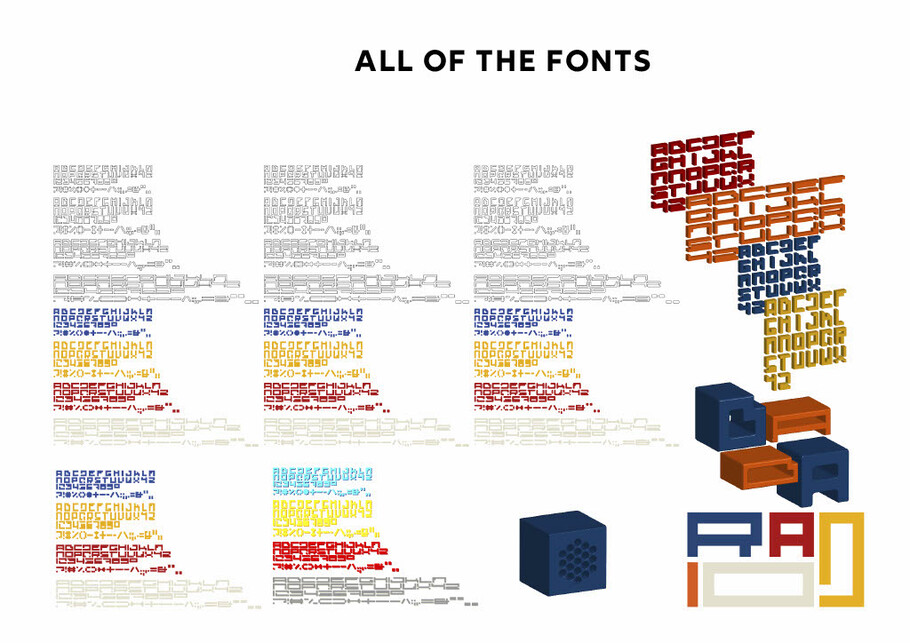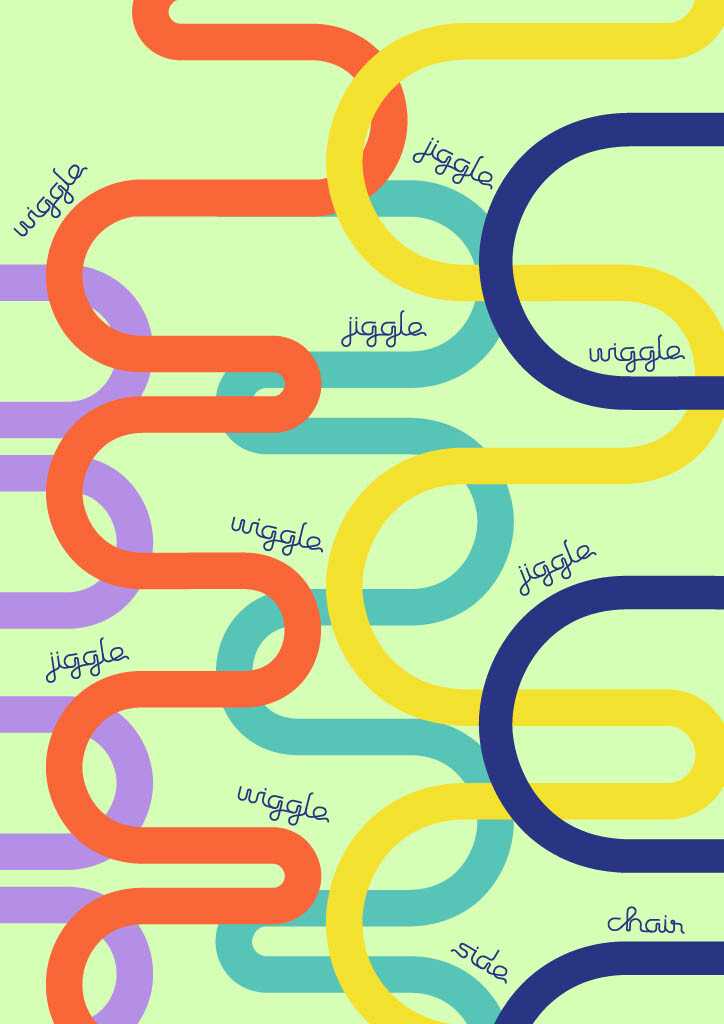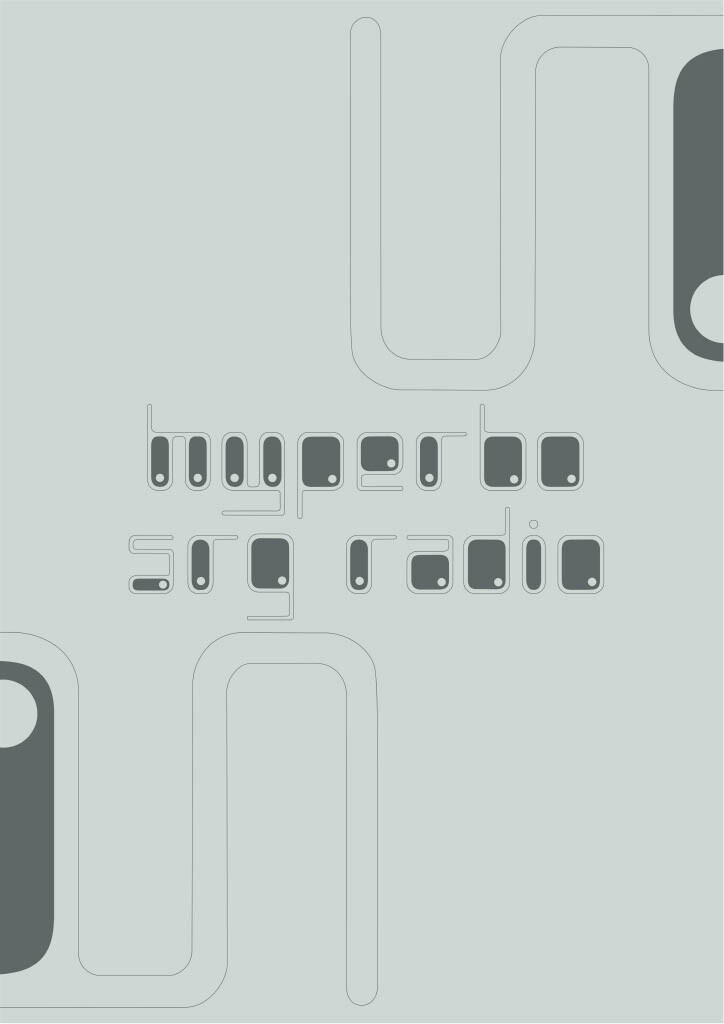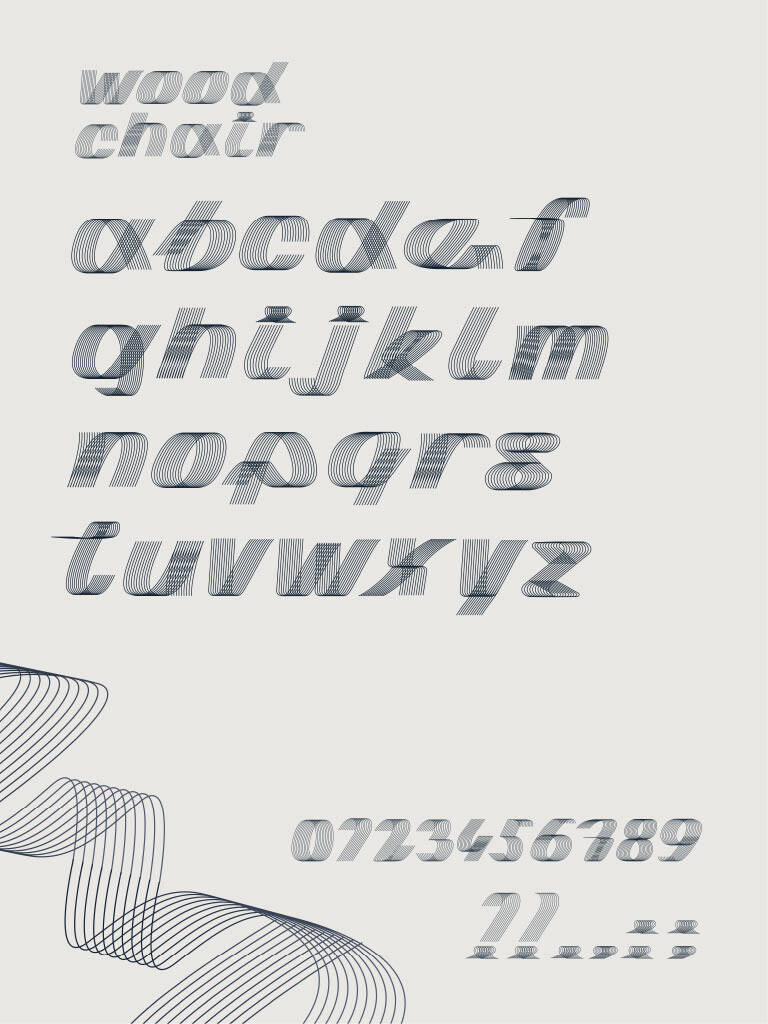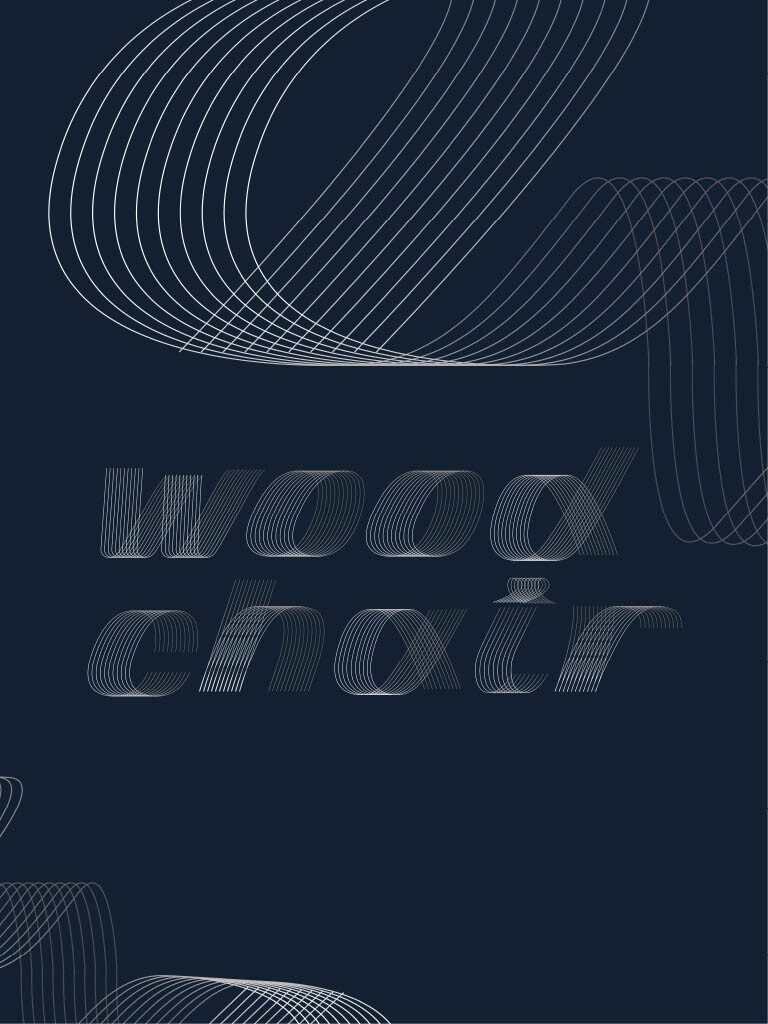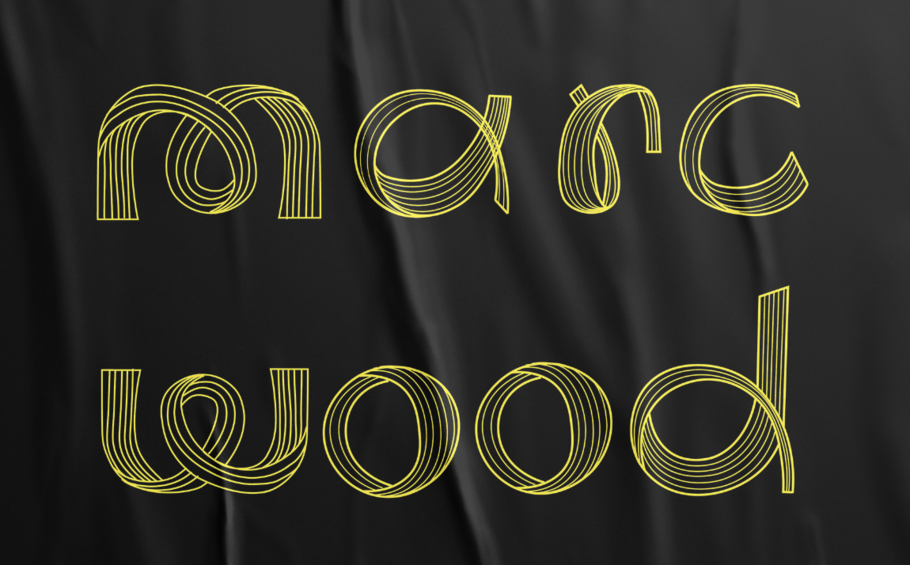
Monotype y Middlesex.
« El trabajo del alumnado es digno de admiración. Las soluciones tipográficas que nos proponen desde sus innovadores puntos de vista suelen sorprendernos, y con buenas ideas, inspiración real y orientación, surgirán grandes proyectos en el futuro. »
Emilios Theofanous, diseñador tipográfico de Monotype
Este año, hemos tenido el placer de colaborar con Middlesex University y el módulo sobre tipografía de Andy Gossett. Phil Garnham (director creativo de tipografía y antiguo alumno de Middlesex) y Emilios Theofanous (diseñador tipográfico de Monotype) tuvieron la oportunidad de mantener dos sesiones online, una para iniciar el proyecto y otra más adelante durante el semestre para hablar sobre el proceso, comentar los diseños y resolver dudas relacionadas con el diseño tipográfico.
Diseñar un tipo de letra durante un semestre académico no es tan fácil como podría parecer; especialmente, en este último año, en el que las sesiones han tenido lugar online y las interacciones entre estudiantes han sido limitadas. Por ello, el trabajo del alumnado es digno de admiración, y las soluciones tipográficas que nos proponen desde sus innovadores puntos de vista suelen sorprendernos. Es probable que no todas funcionen directamente en un entorno comercial, pero con buenas ideas, inspiración real y orientación, surgirán grandes proyectos en el futuro. El alumnado de tercer año de Diseño Gráfico no ha sido ninguna excepción este curso: todo el mundo se ha remangado y ha puesto un gran entusiasmo y curiosidad en el proyecto, mostrando su voluntad de experimentar y descubrir este fantástico mundo de la creación de letras.
Durante nuestra primera sesión online, hablamos sobre algunos principios básicos del diseño tipográfico y las tendencias actuales, y analizamos su encargo creativo.
El encargo creativo:
El alumnado debía elegir un objeto entre una selección de diseños de productos célebres, como muebles, maquinaria, utensilios y electrodomésticos, y desarrollar una nueva marca tipográfica para él. El objetivo era llevar sus ideas iniciales a un diseño de fuentes plenamente funcional.
Taller conceptual:
Después de unas semanas, volvimos a reunirnos para hablar sobre el proceso. Fue muy interesante ver cómo transformaron en formas tipográficas el objeto que habían elegido para inspirarse. En muchos casos, eran representaciones muy literales e ilustrativas, mientras que en otros eran más modulares y a menudo ilegibles. Es importante comprender el contexto de estas propuestas iniciales. Como parte de la identidad de una marca, es habitual que pertenezcan al género de la tipografía display y que guarden relación con el diseño gráfico, por lo que nuestras sugerencias debían guiar al alumnado sobre cómo proceder y hacer que sus ideas fueran más útiles y adecuadas para el mundo real de las marcas. Hablamos sobre la importancia de la legibilidad; por ejemplo, mencionamos qué aspectos deben tenerse en mente al pasar de un logo a un tipo de letra y cómo la coherencia entre formas tipográficas similares puede ser la clave para crear armonía y ritmo tipográfico. Algunos de los diseños eran como un boceto de la tipografía, basados en un esqueleto sin mucho peso. Por ello, hablamos sobre la idea del peso y la escala, de la función que desempeña el tamaño de la tipografía, las situaciones en las que se usaría y cómo quedaría al imprimirla o mostrarla en distintos medios.
Los tipos de letras:
A lo largo de otras tres semanas bajo la dirección de Andy Gossett, los estudiantes desarrollaron sus conceptos en alfabetos de la A a la Z, números y puntuación sencilla. Todos los tipos de letras se enviaron para revisión y ya podemos mencionar algunos de nuestros favoritos: